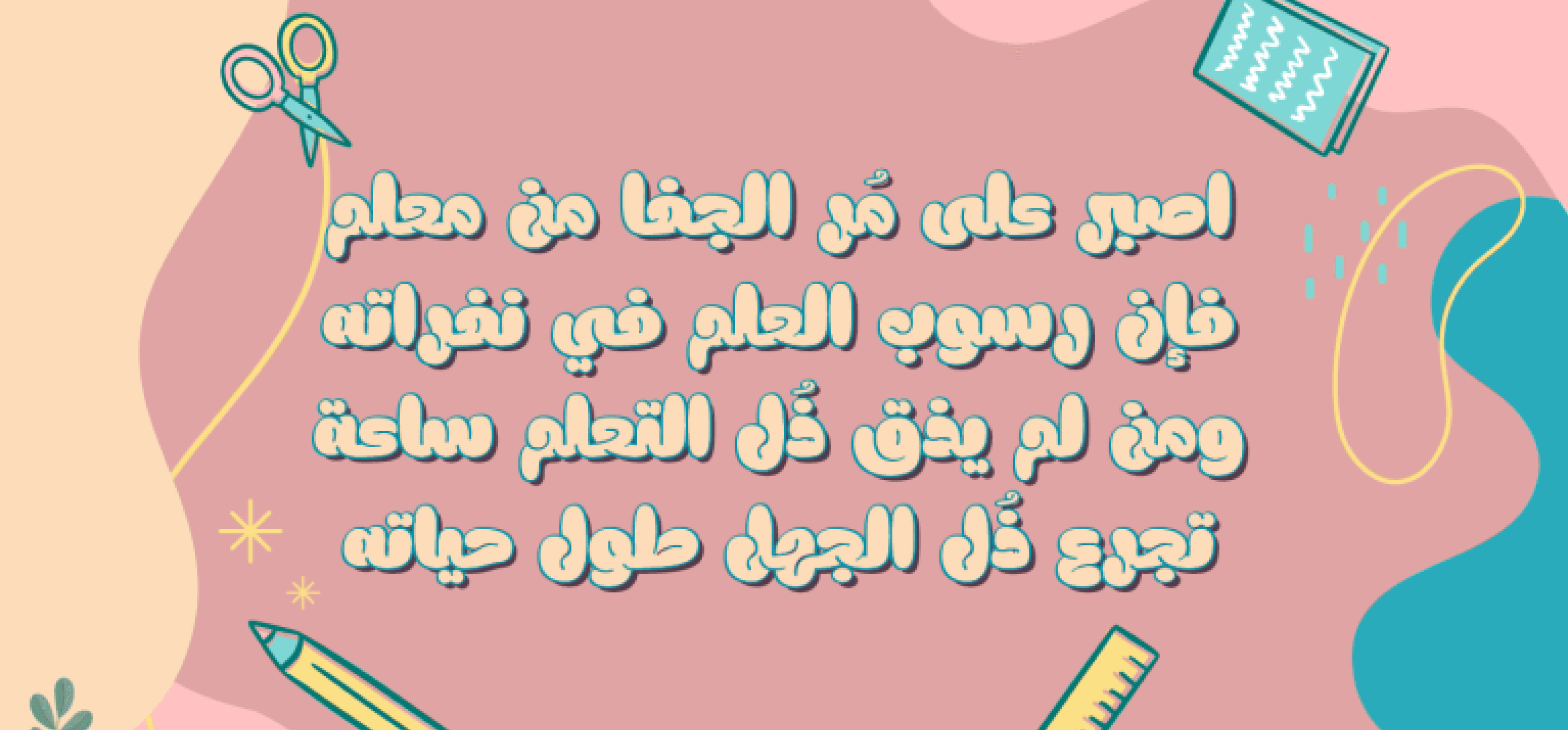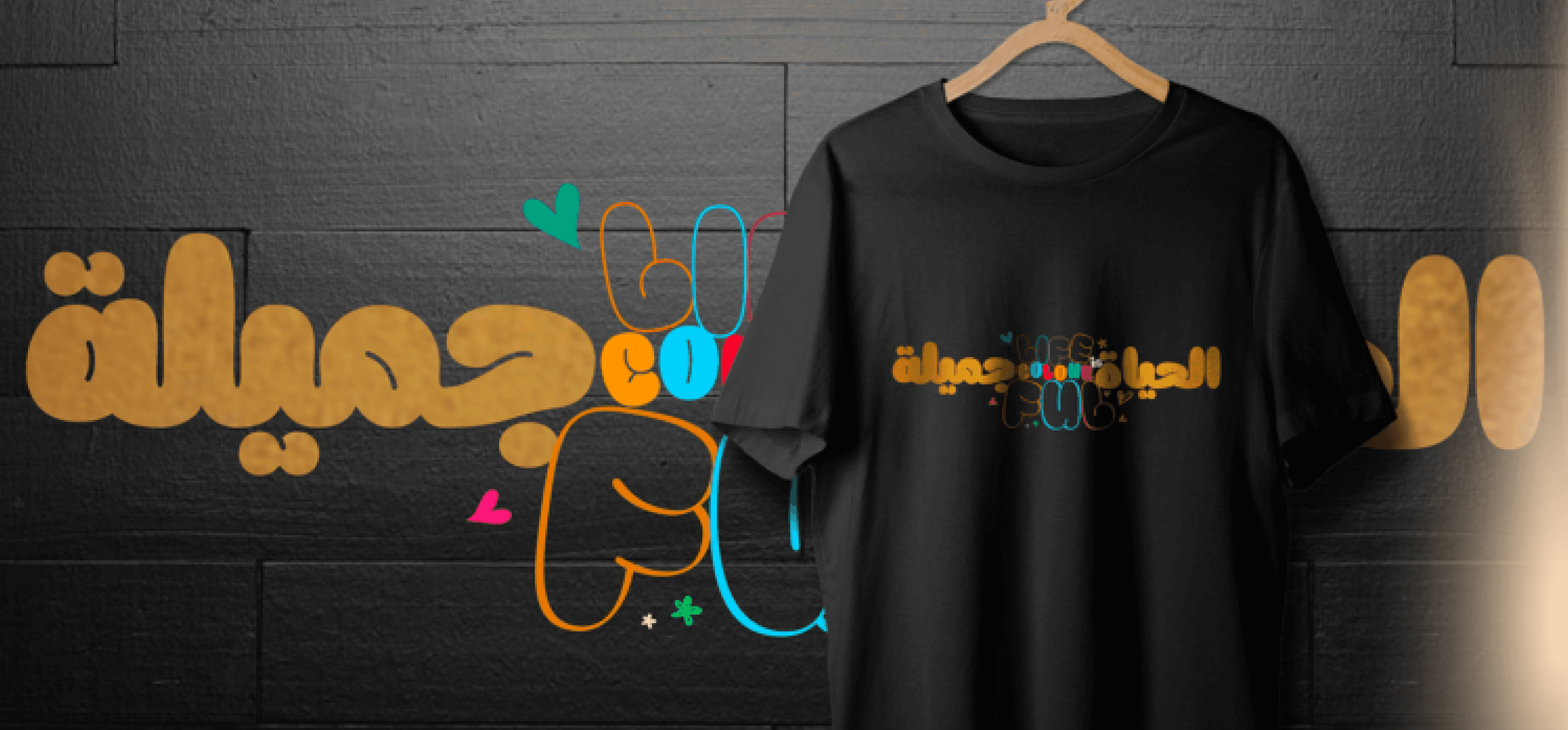
خط Meila هو خط مرح ولطيف، يتميز بحروف عريضة وجذابة بصريًا.
يحتوي الخط على خطوط ناعمة على كل جانب، خاصة من الخارج، مع غياب شبه كامل للزوايا الحادة. أما من الداخل، فتوجد خط واحد فقط يعمل كمساحة داخلية للحرف (counter space).